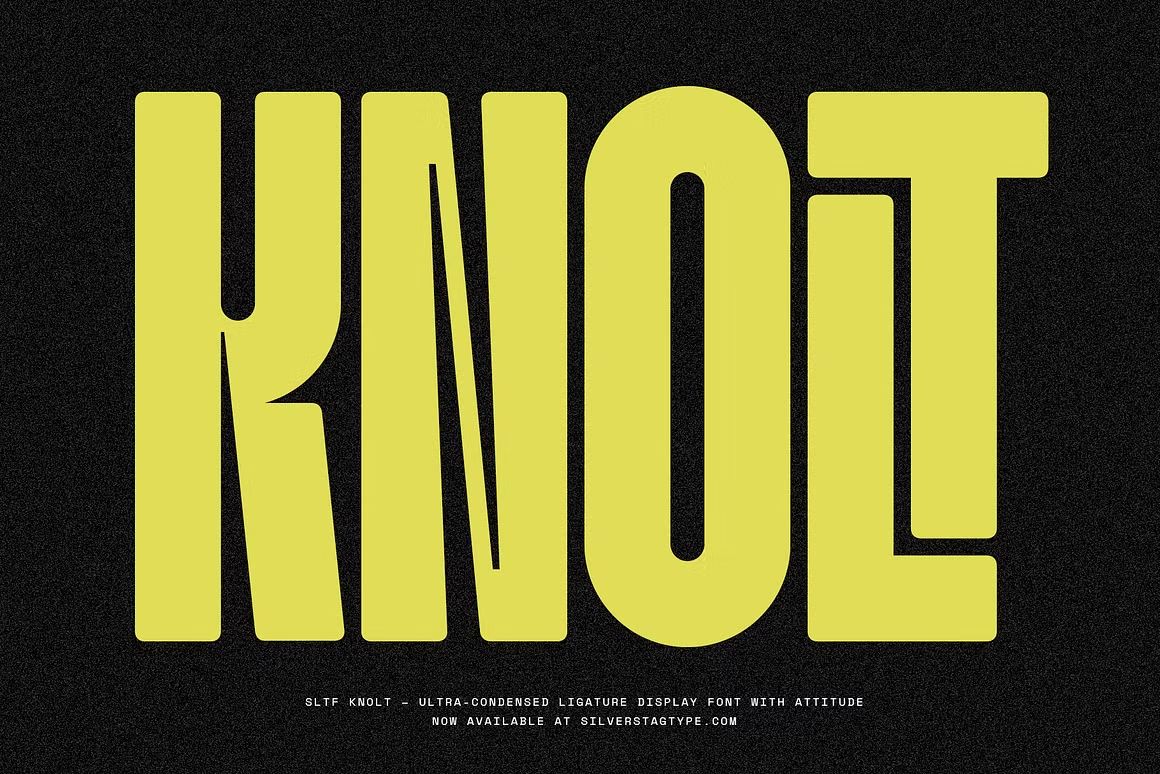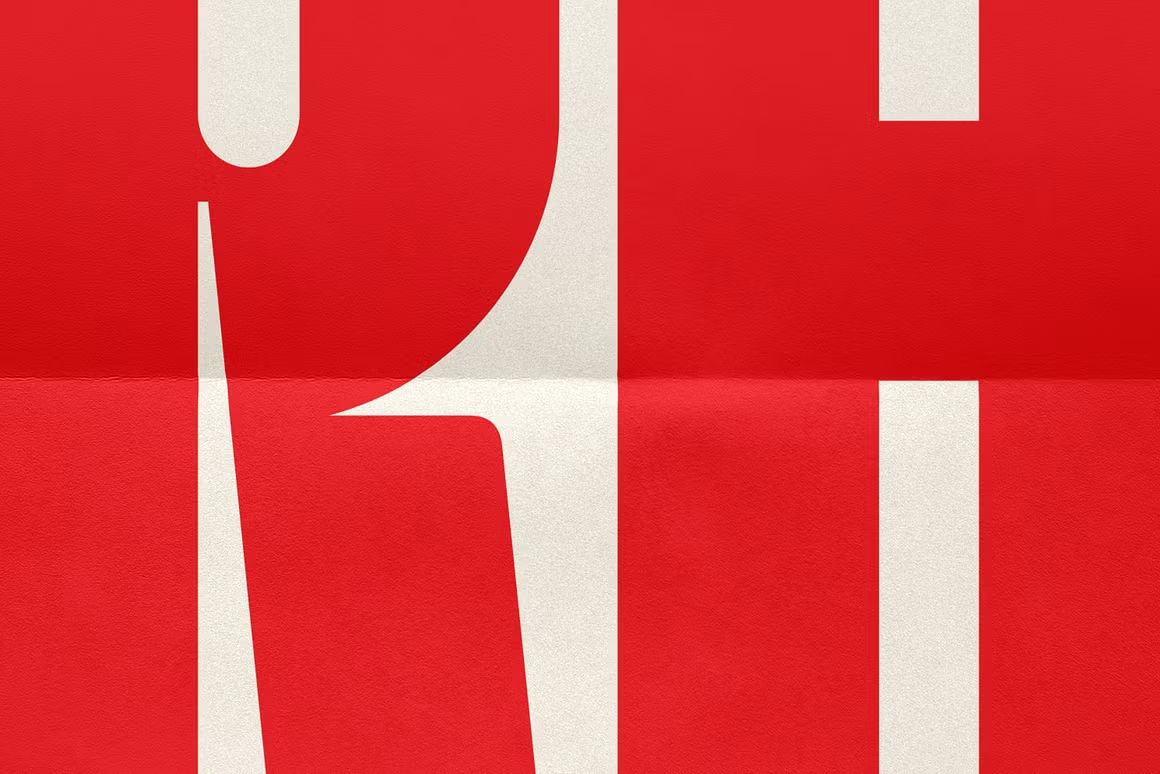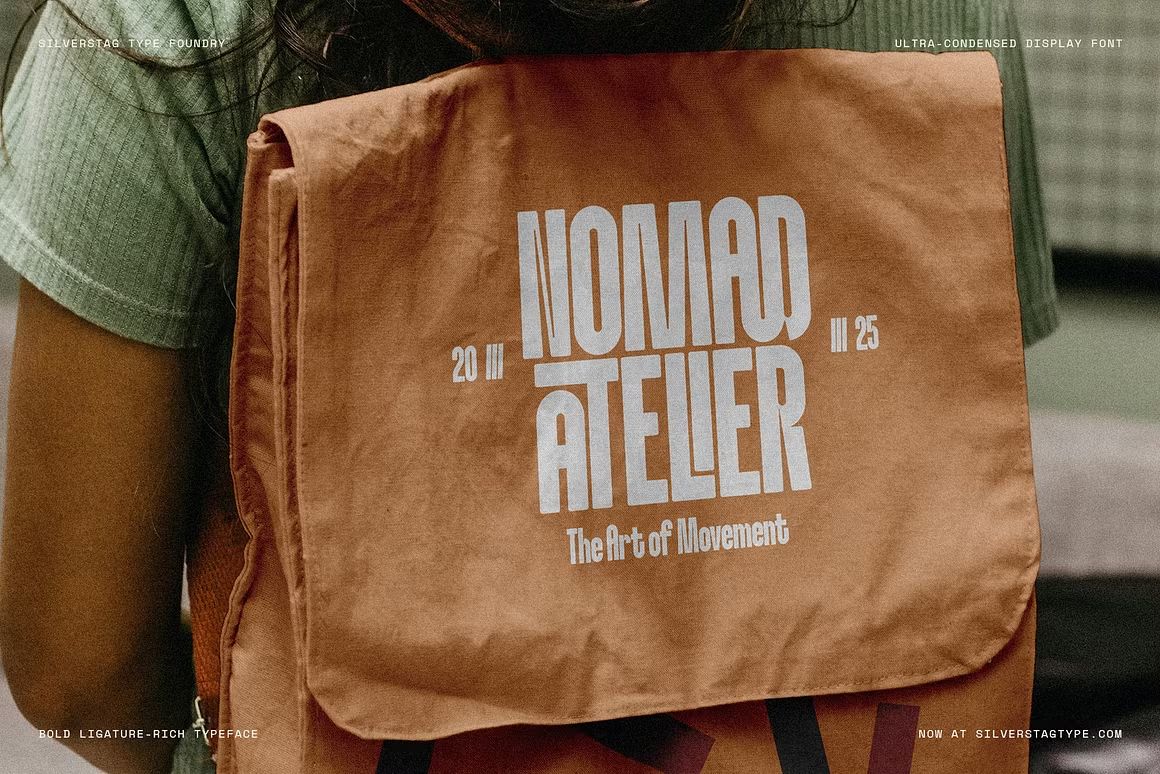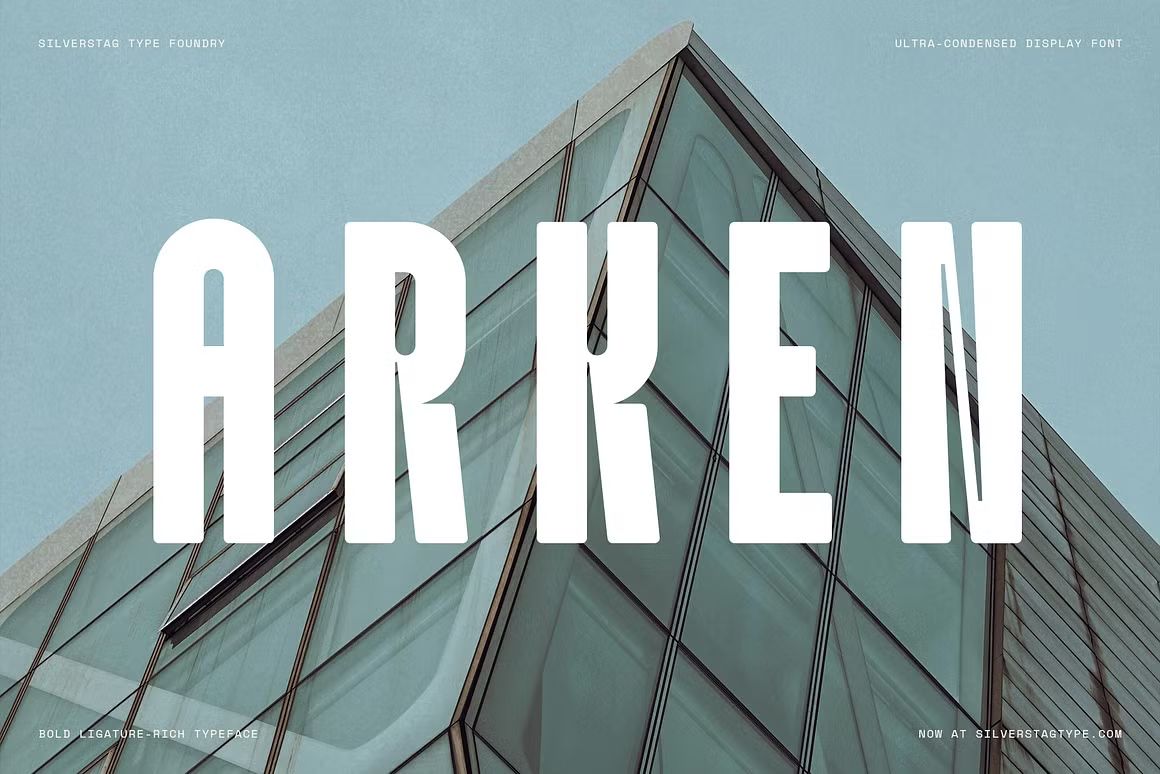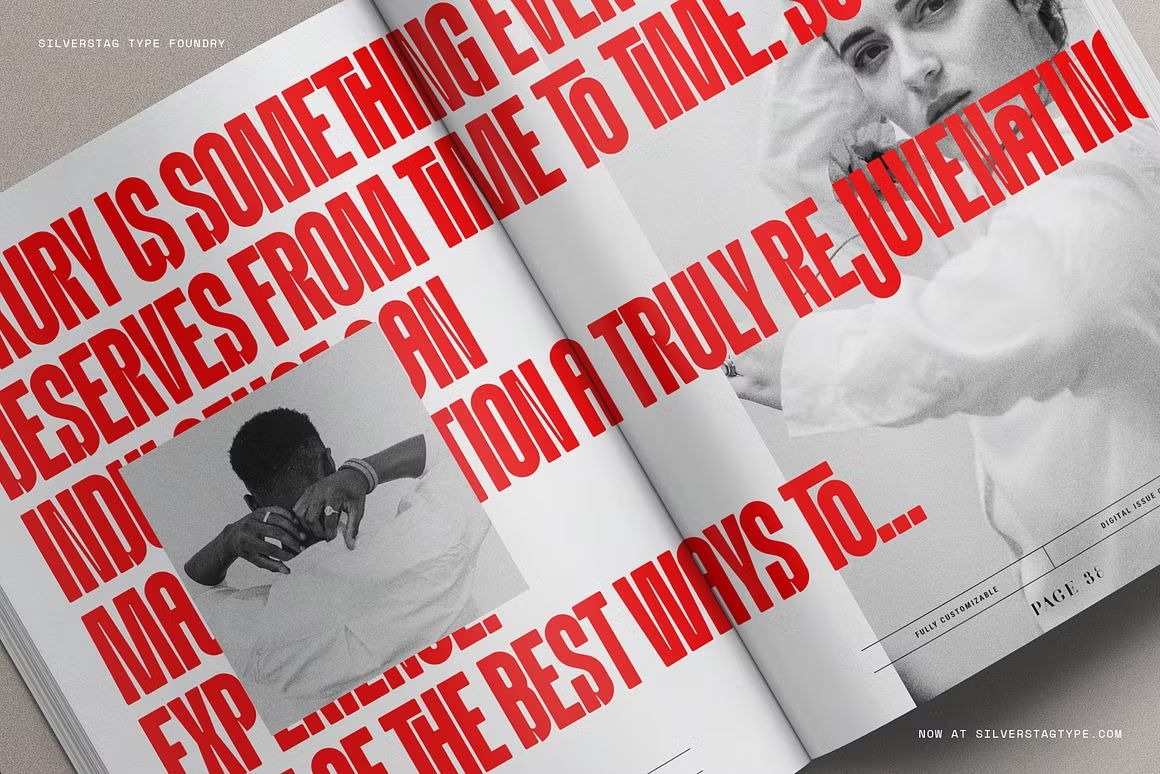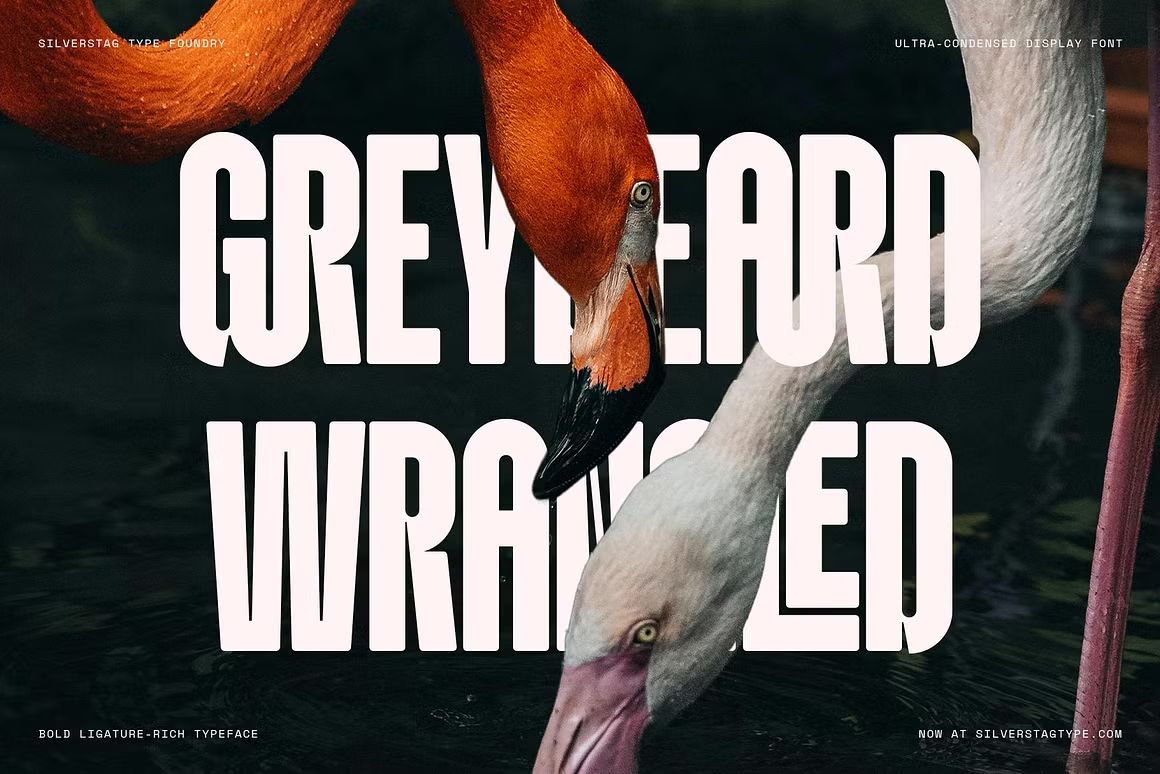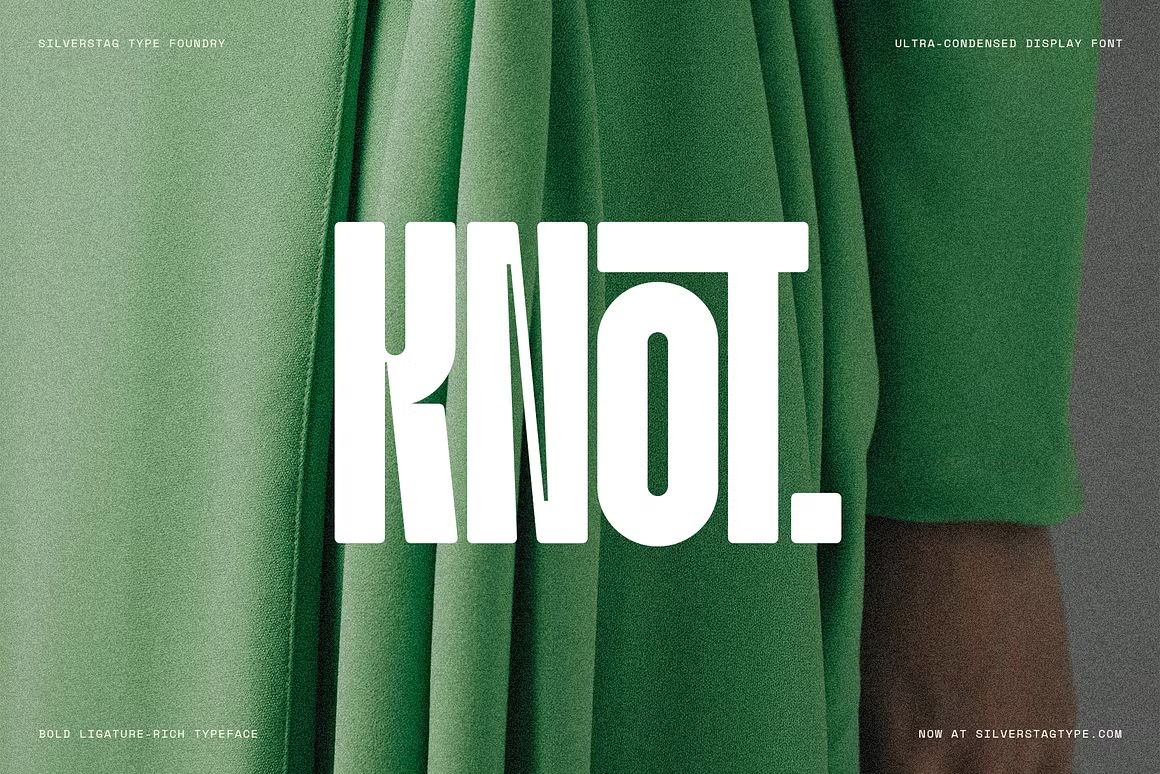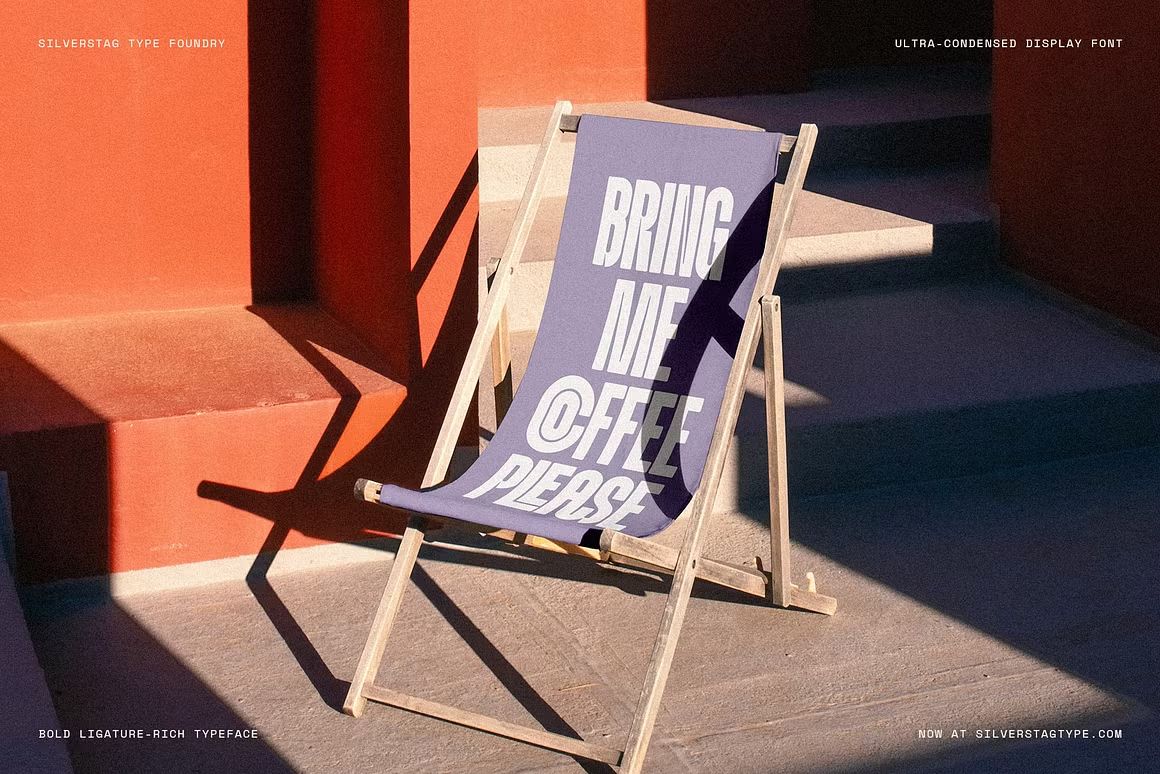
Knolt – Bold Ultra Sans Serif Font
Knolt adalah font sans serif ultra bold yang kuat dan modern, cocok untuk headline dan desain mencolok. Format OTF/TTF/WOFF, siap digunakan di berbagai proyek.
Knolt adalah font sans serif ultra bold yang dirancang untuk membuat pernyataan visual yang kuat dan mencolok. Dengan bentuk huruf yang solid, geometris, dan modern, Knolt sangat cocok untuk headline, poster, branding, kemasan produk, dan desain digital yang membutuhkan tipografi tegas dan penuh karakter. Tampilannya yang tebal memberikan kesan percaya diri dan kontemporer.
• Ultra bold sans serif dengan desain geometris dan modern
• Ideal untuk headline, branding, dan poster mencolok